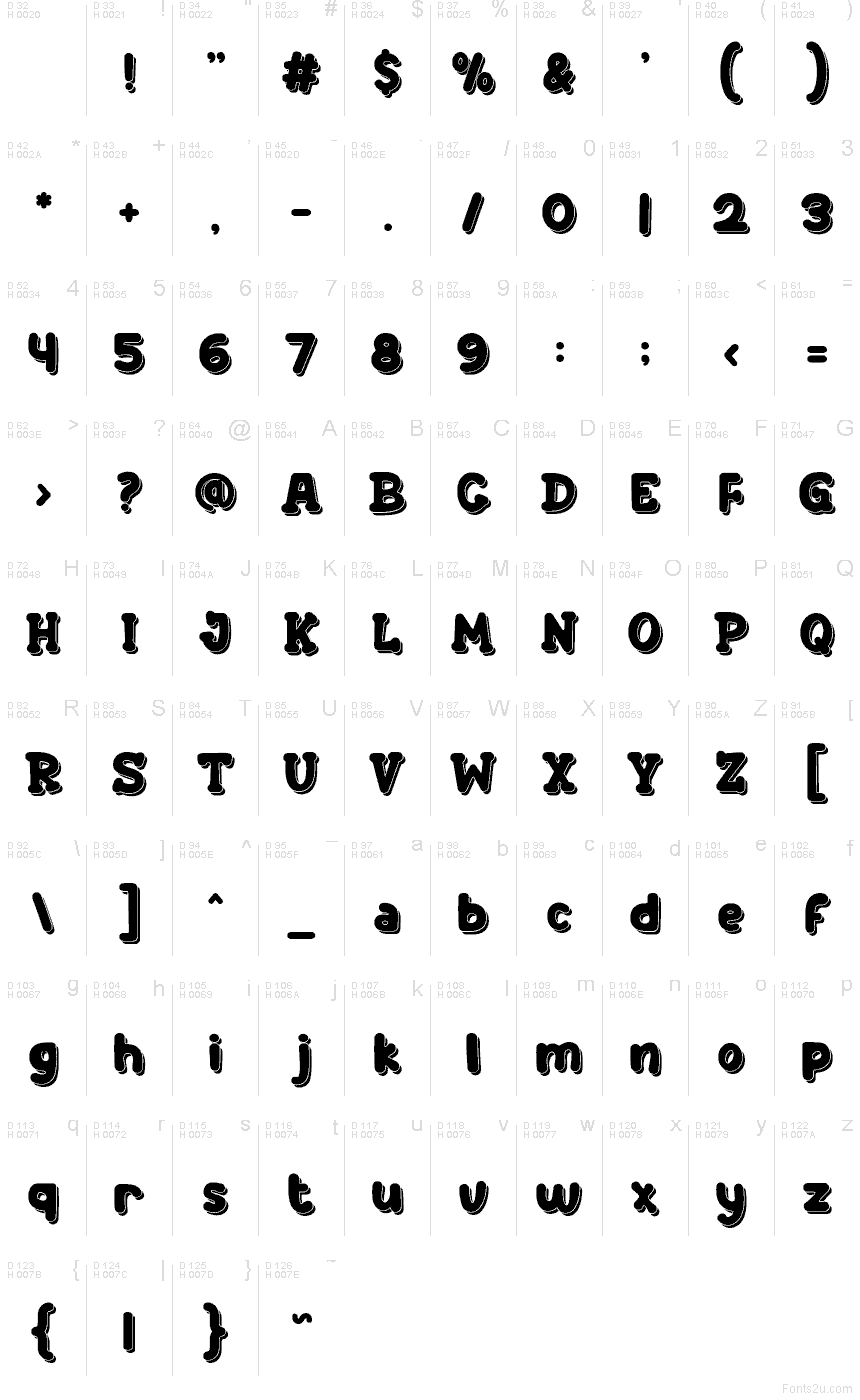
Crayon Craft Three von Putracetol Studio ist eine kostenlose Display-Schriftart im Wachsmalstift-Stil, die durch ihre geschwollenen, abgerundeten Formen und ein versetztes Highlight im Inneren besticht. Dieser Effekt lässt die Buchstaben handgezeichnet und weniger digital-glatt wirken. Die doppelte Konturführung verleiht dem Alphabet einen weichen, puffigen Rhythmus, der eher an ausgeschnittenes Papier oder Markermarkierungen erinnert als an eine standardmäßige „Bubble“-Schrift.
Ob Schulplakate, Lernblätter für Kinder, kreative Verpackungen, Einladungen oder verspielte Social-Media-Grafiken – diese Schrift passt perfekt. Die breiten Silhouetten machen kurze Überschriften lebendig, während die skizzenhaften Innenkanten für einen hausgemachten Look sorgen, der ideal zu kreativen Projekten für ein junges Publikum passt.